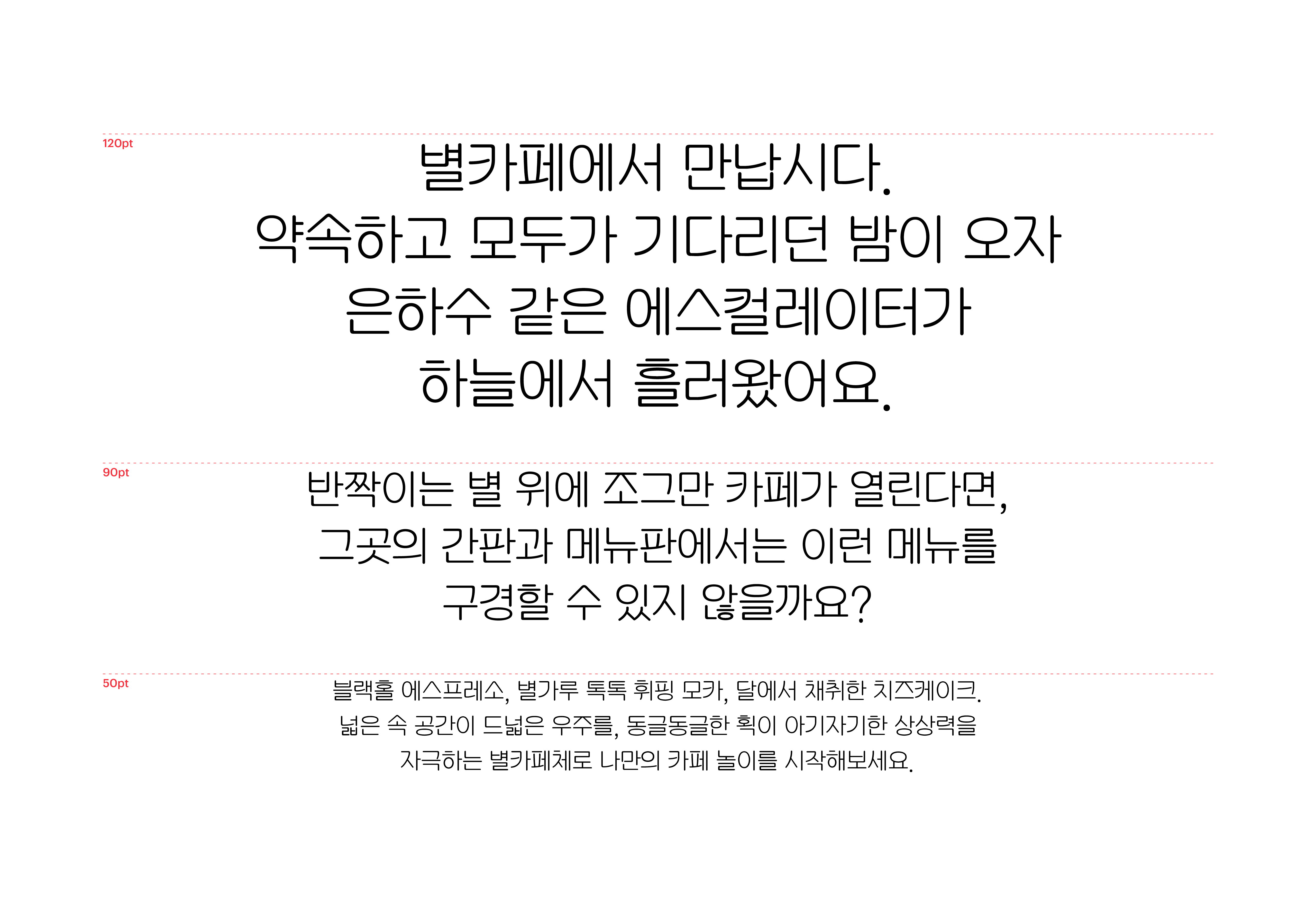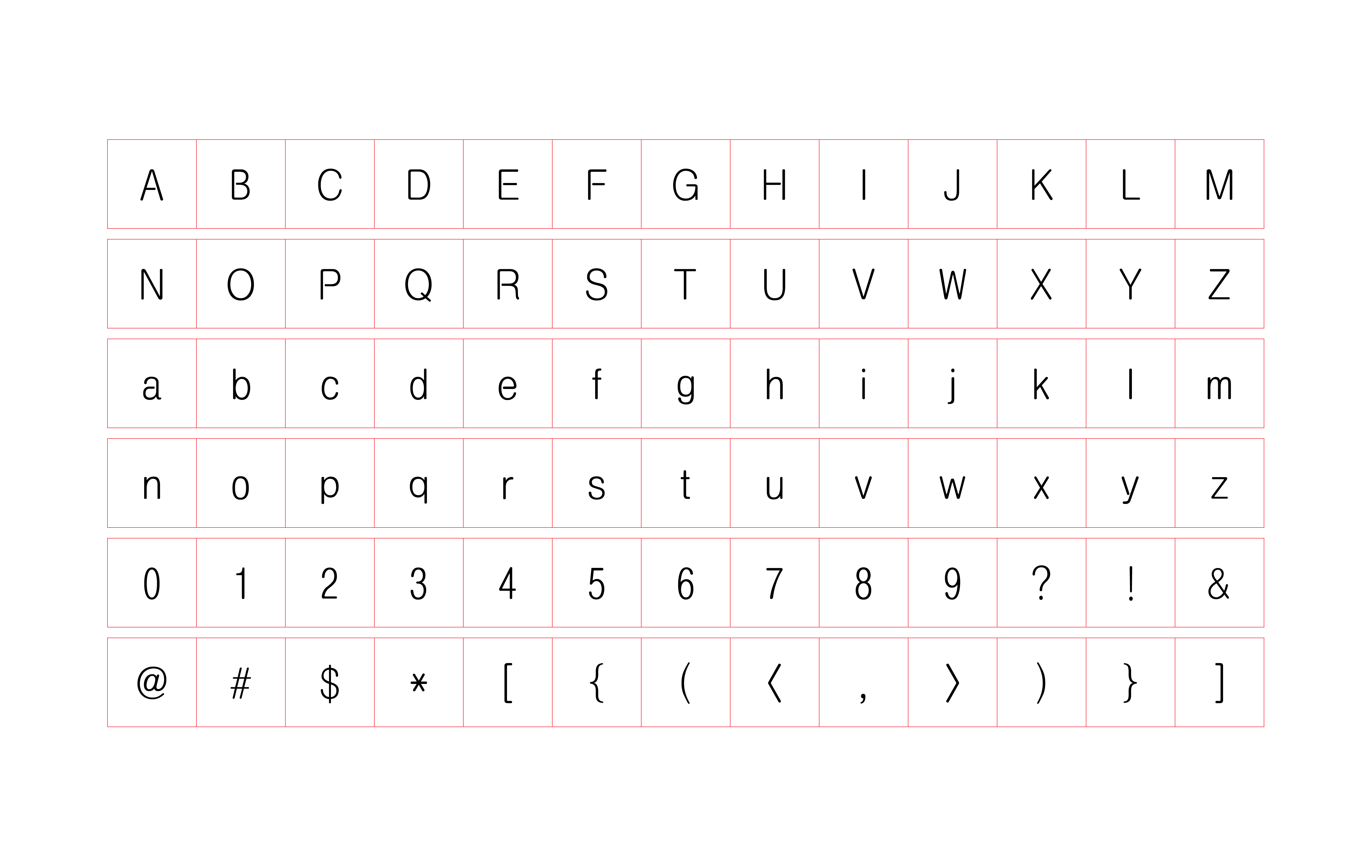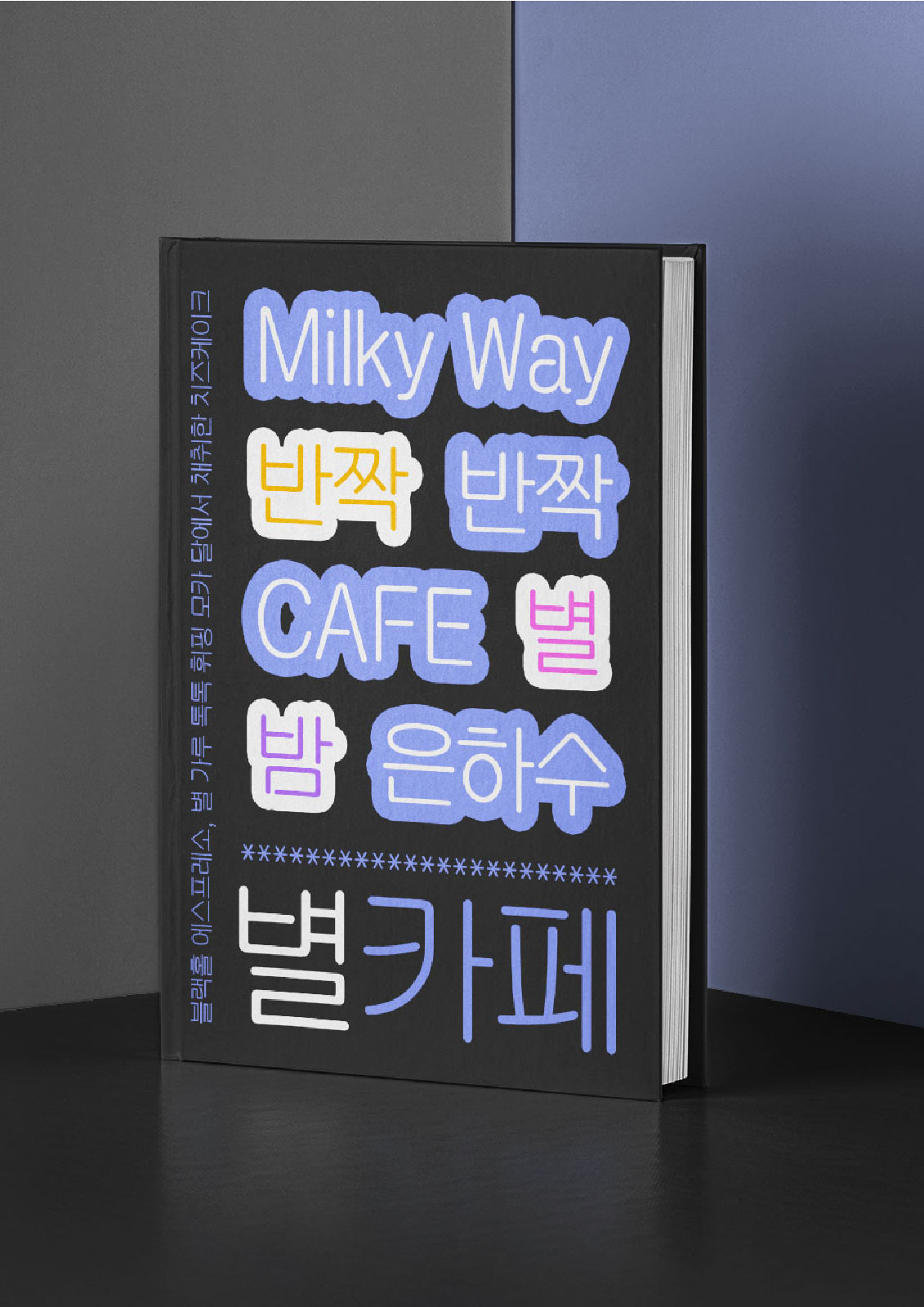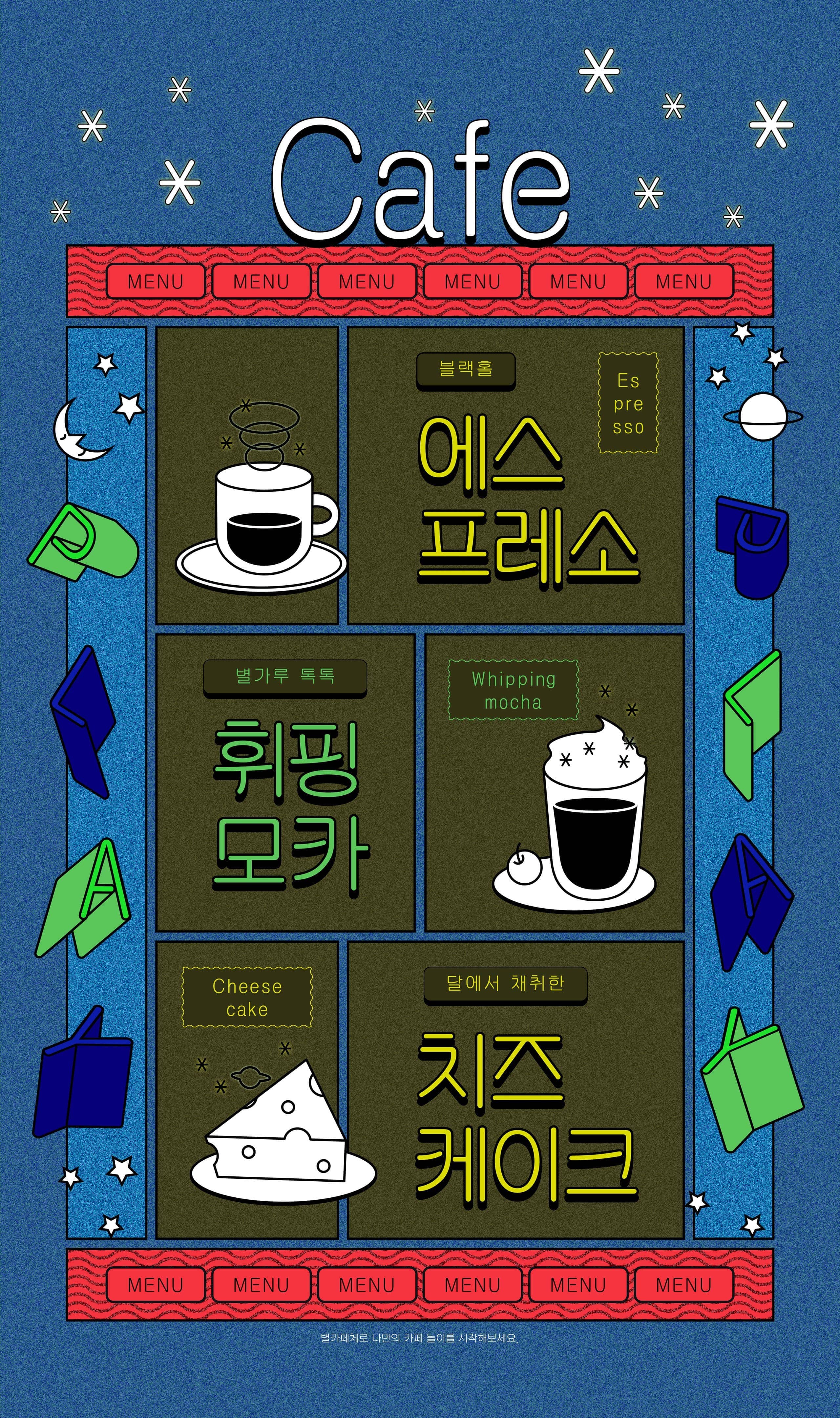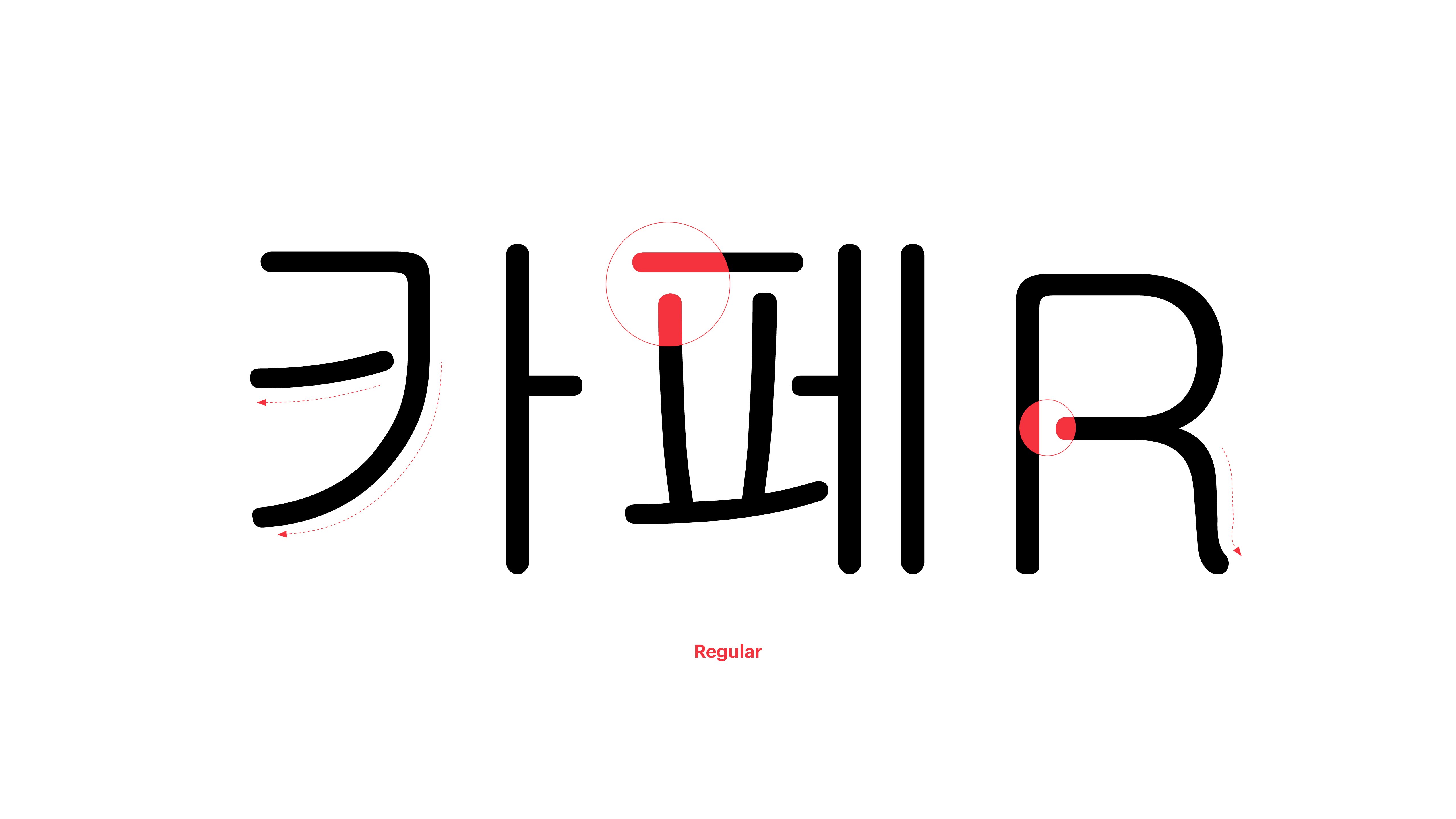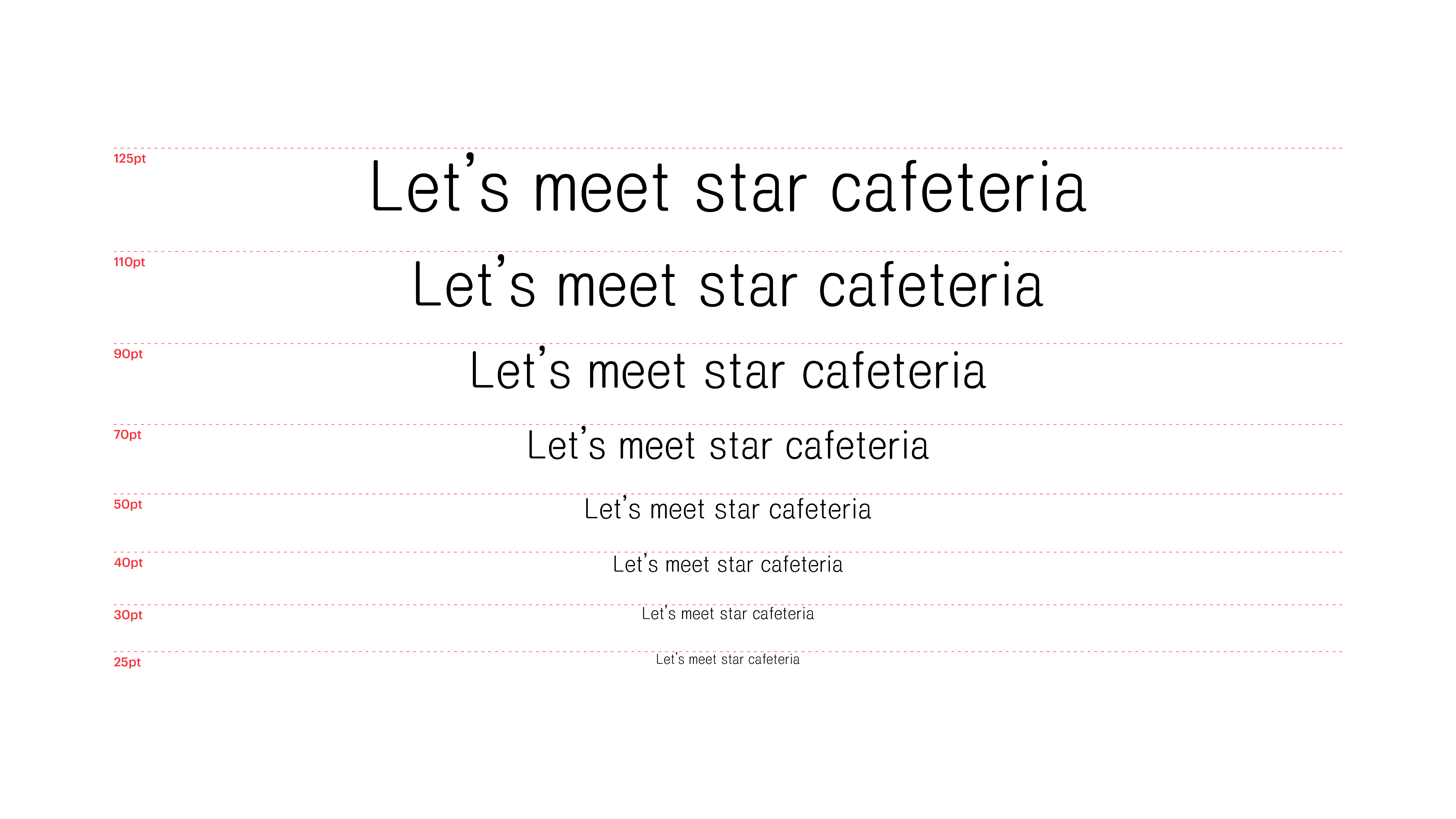
별카페
Yoon 별카페
반짝이는 별 위에 조그만 카페가 열린다면, 그곳의 간판과 메뉴판에서는 이런 메뉴를 구경할 수 있지 않을까요? 블랙홀 에스프레소, 별 가루 톡톡 휘핑 모카, 달에서 채취한 치즈케이크. 어떤 메뉴라도 좋아요! 넓은 속 공간이 드넓은 우주를, 동글동글한 획이 아기자기한 상상력을 자극하는 별카페체로 나만의 카페 놀이를 시작해보세요.